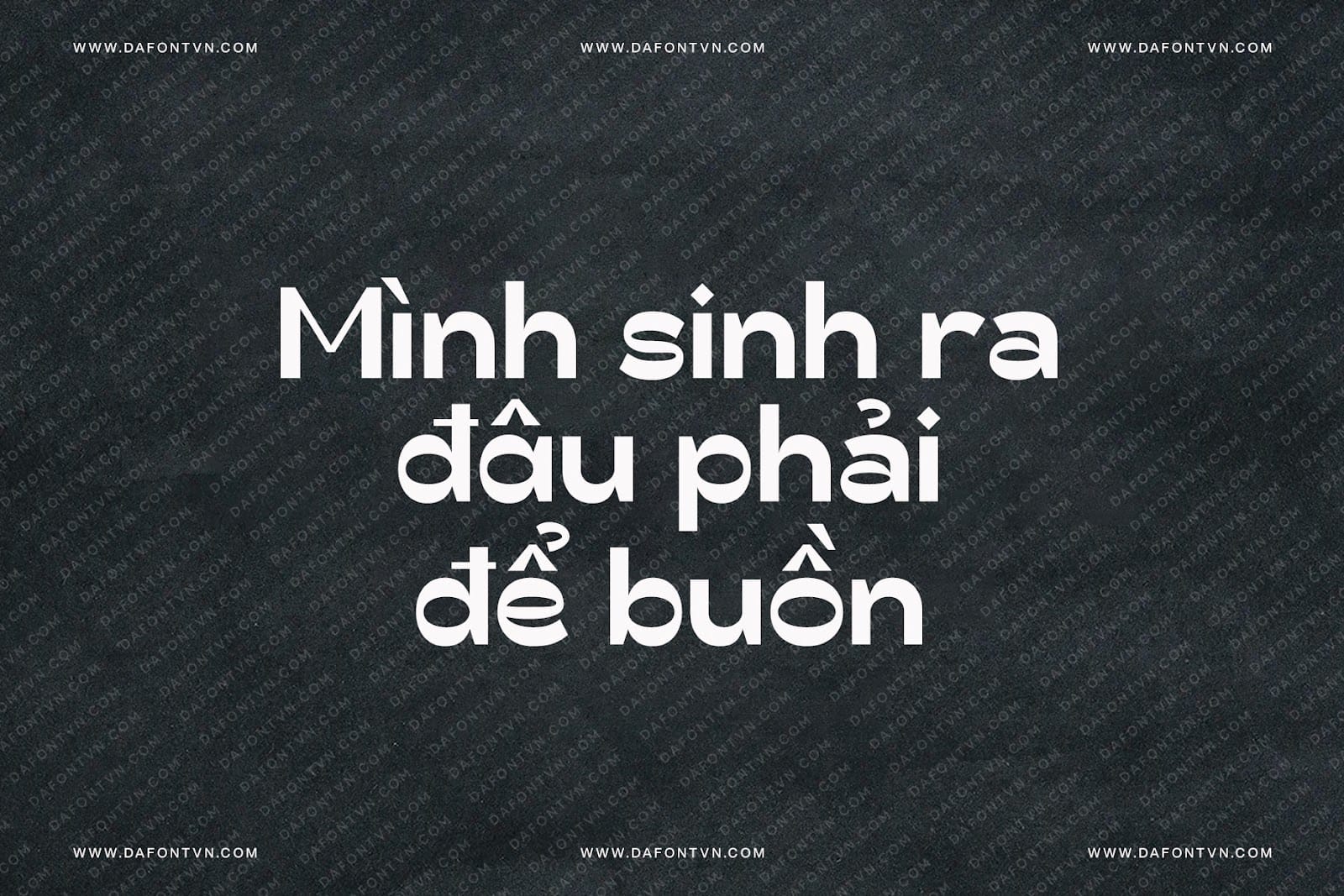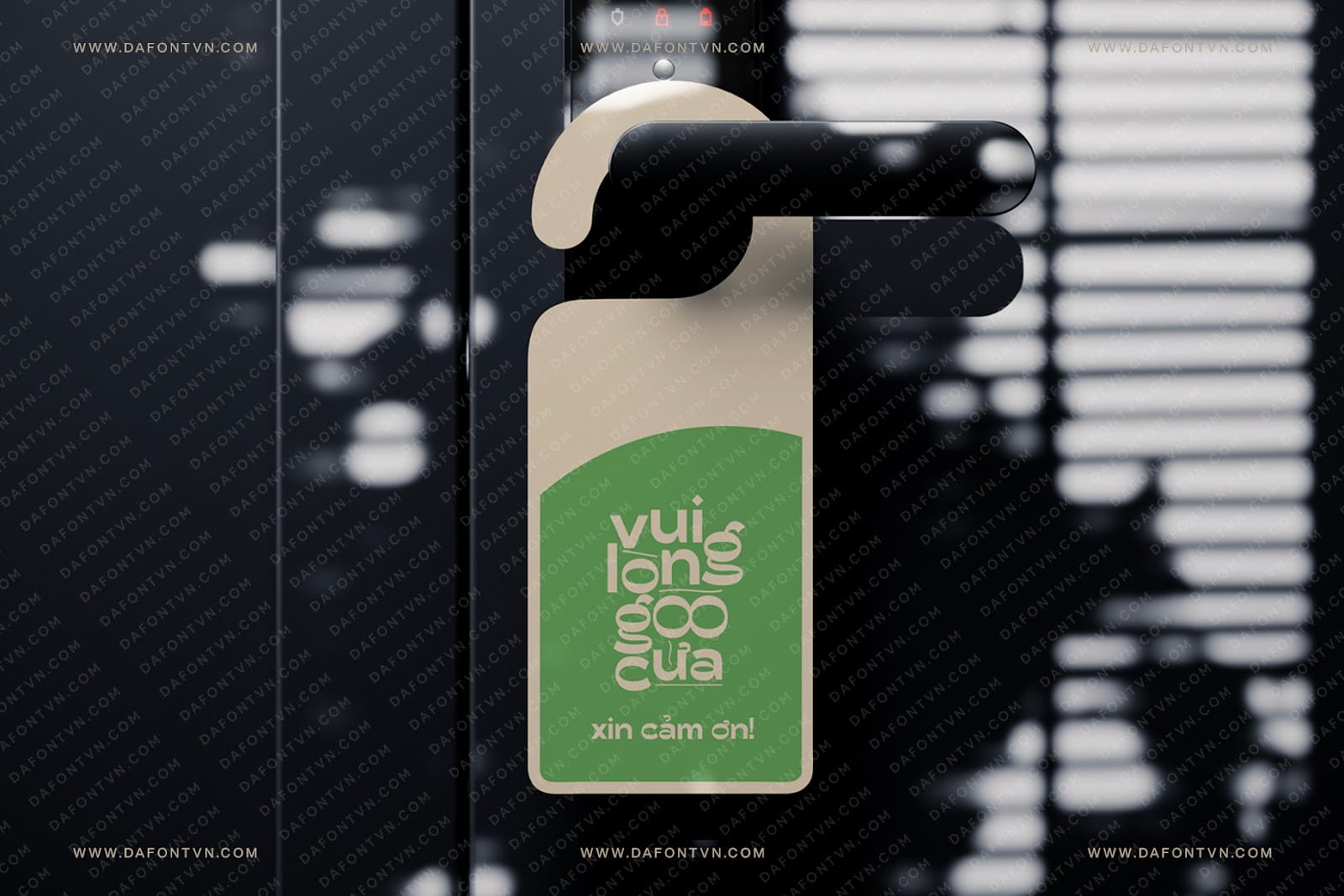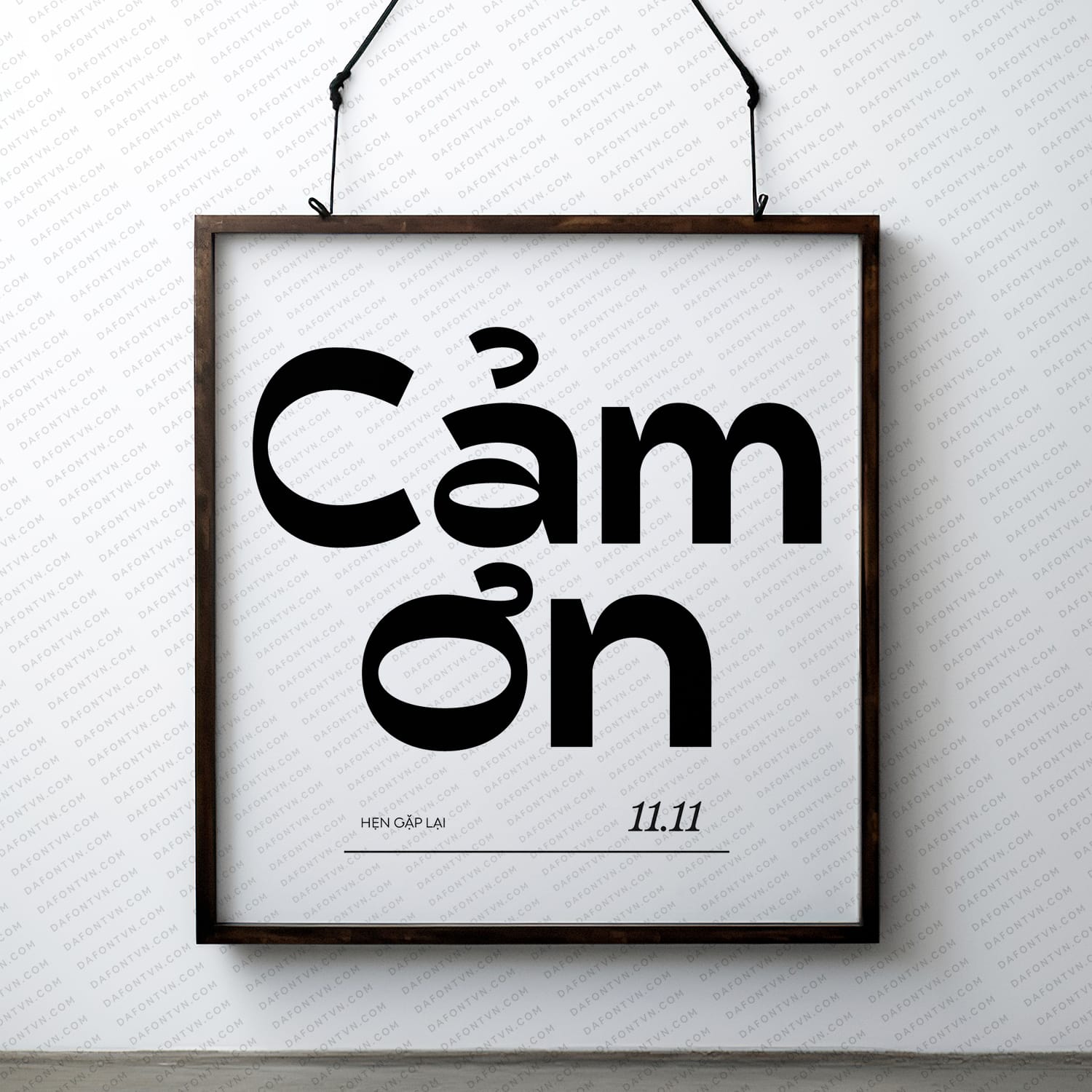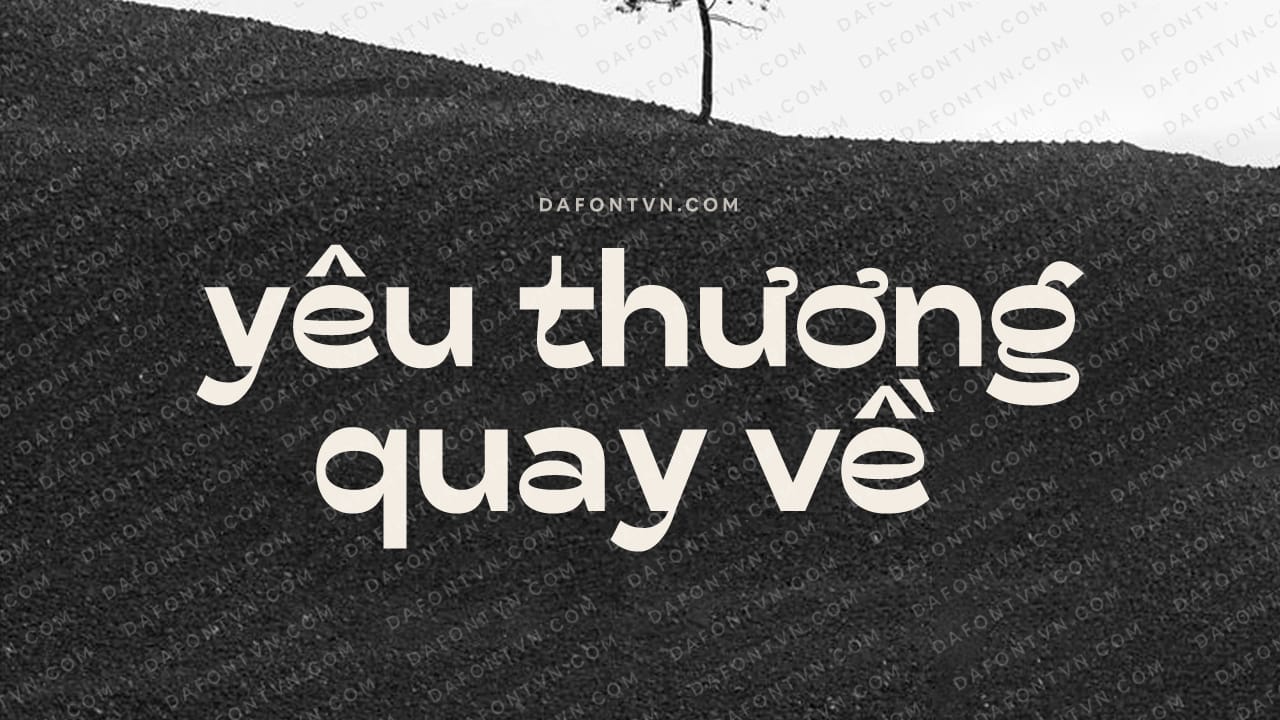
Float font là một kiểu chữ ấn tượng đưa bạn vào một cuộc hành trình thú vị quay trở lại kỷ nguyên disco của những năm 70.
Với các giác cứng cáp và thẩm mỹ, nó là sự lựa chọn hoàn hảo để thêm chút quyến rũ cổ điển vào thiết kế của bạn. Mỗi chữ cái dường như đang nhảy múa và lắc lư, giống như quả cầu disco mang tính biểu tượng.
Cho dù bạn đang thiết kế áp phích, bìa album, sự kiện, logo, quảng cáo hay bất cứ thứ gì cần chút hoài niệm về vũ trường, về những gì cổ điển, Float sẽ làm cho văn bản của bạn nổi bật và như đưa bạn thẳng đến sàn nhảy của quá khứ.
Ngoài ra, Float là kiểu chữ nổi bật với các nét dày và đậm vì vậy nó cũng rất thích hợp cho các thiết kế hiện đại ngày nay như poster, bìa sách…